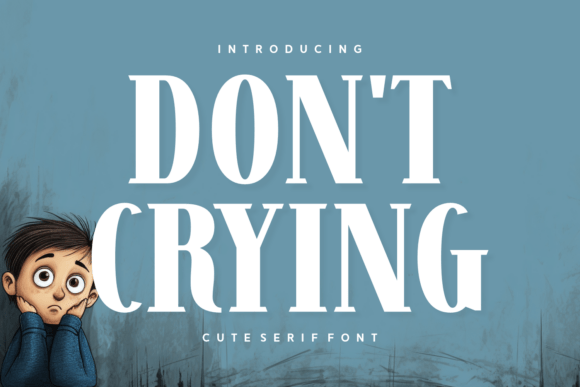
Don't Crying
適切なデザイン要素を見つけるのは難しい場合がありますが、Don't Cryingは作品を即座に引き立てる優れたコレクションを提供します。
POD(オンデマンド印刷)製品、結婚式の招待状、またはソーシャルメディアのグラフィックを作成している場合でも、Don't Cryingは理想的です。